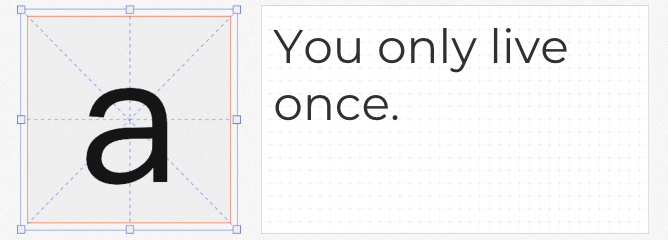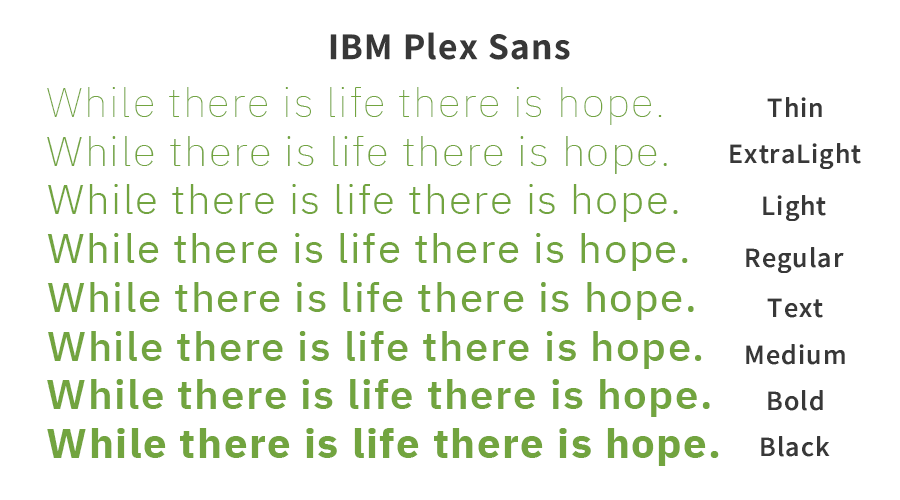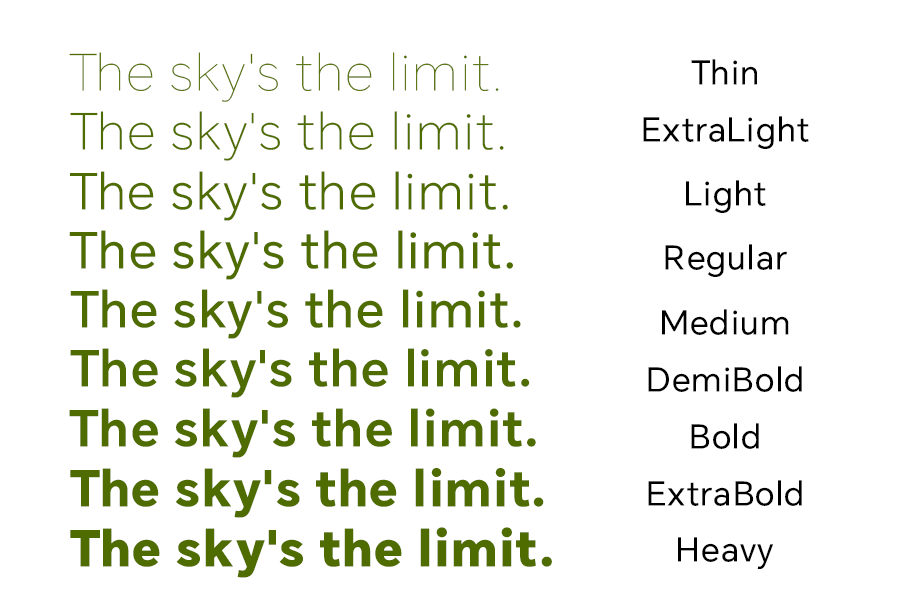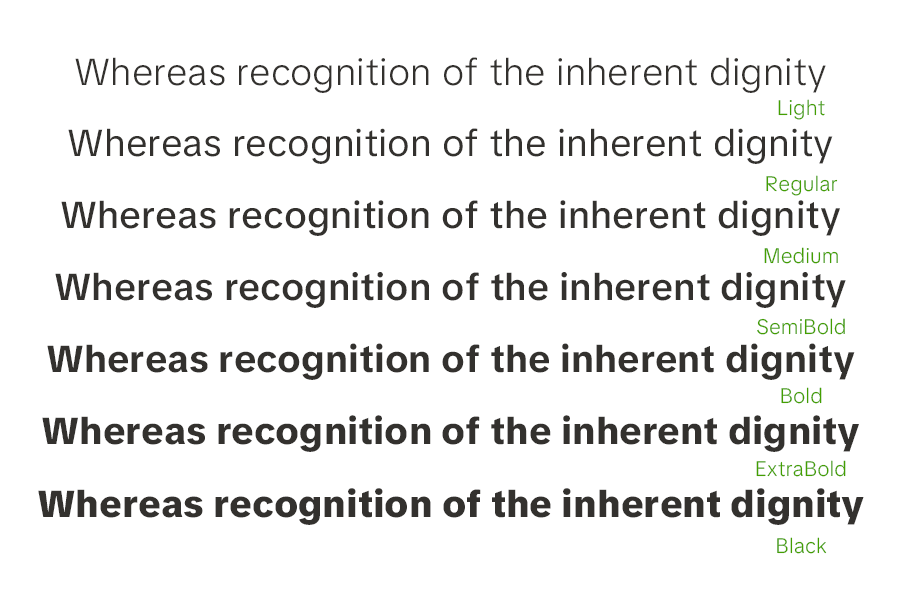
在视觉设计领域,字体的选择直接影响信息传递的质感与风格。对于追求高效与创意的设计师而言,免费可商用的优质无衬线西文字体是不可或缺的资源。以下四款兼具美学与功能性的字体,覆盖从动感社交到科技商务的多元场景,助你轻松提升设计品质。
1. TikTok Sans
作为TikTok平台默认字体,TikTok Sans以俏皮、清新、充满动感的设计语言成为短视频字幕的绝佳选择。7款字重与可变字体版本支持灵活调整,无论是快节奏的舞蹈视频还是轻松的生活vlog,其圆润的笔画与适度的倾斜角度都能强化视觉流动性,让文字与画面形成自然互动。
2. HONOR Sans
这款以黑体为基础的字体,在笔画离散与布白控制上展现出惊人的精致度。通过优化字符内部空间与部件比例,HONOR Sans既保留了传统书法的韵律感,又以几何化的结构适配数字屏幕阅读。其均匀的视觉重量尤其适合品牌视觉系统构建,传递专业与人文并重的品牌气质。
3. Montserrat Regular
受蒙特塞拉特岛建筑启发的Montserrat,以高对比度的直线与几何转角构建出独特的现代感。作为开源字体中的经典之作,其简洁的线条既适合作为正文排版,也能通过加粗字重胜任标题设计。拉丁字母区的独特造型更使其成为文化类、旅游类项目的标志性选择。
4. IBM Plex Sans
作为IBM品牌重塑的核心元素,IBM Plex Sans以理性克制的设计语言诠释企业级美学。相较于Helvetica的保守,其略微加宽的字腔与开放的字怀提升了小字号可读性,而多语言支持与12种字重的完备体系,使其成为科技、金融领域替代付费字体的首选方案。